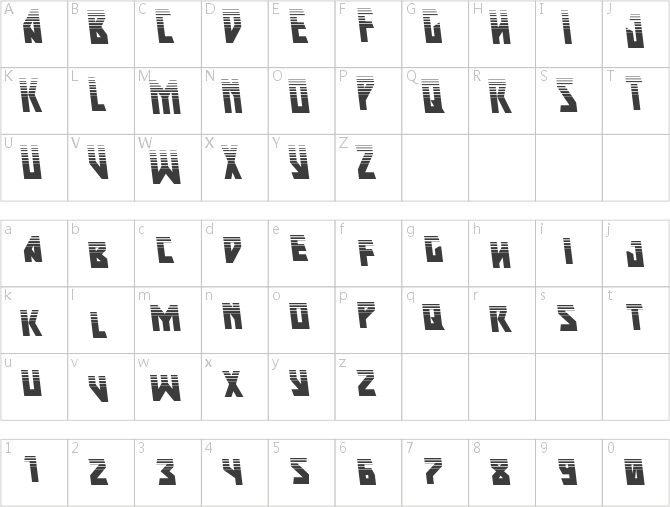
Major Force Halftone Leftalic
Major Force Halftone Leftalic介绍
Major Force Halftone Leftalic字体字库是一款让人赏心悦目、百看不厌的英文字体,适合各类广告和产品包装设计应用,字体大小0.03MB,格式为ttf字体,上传用户是诚泽永信,作者/版权方为未知